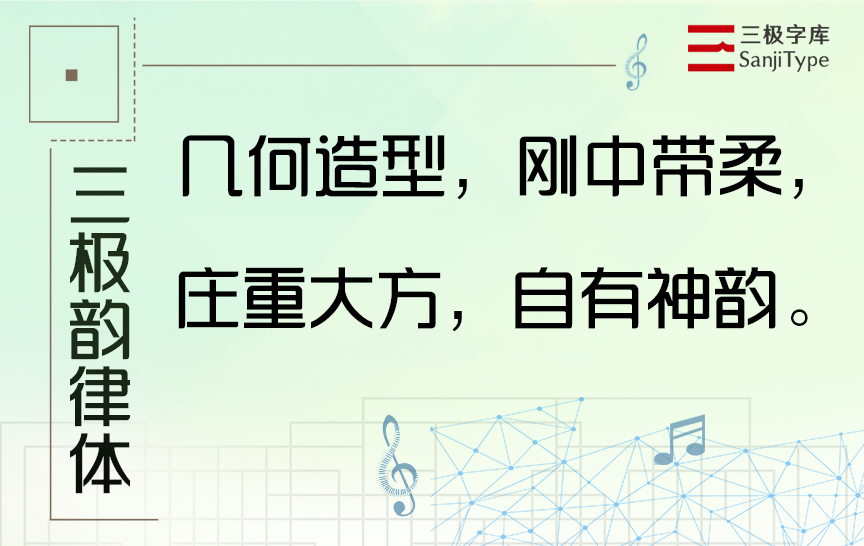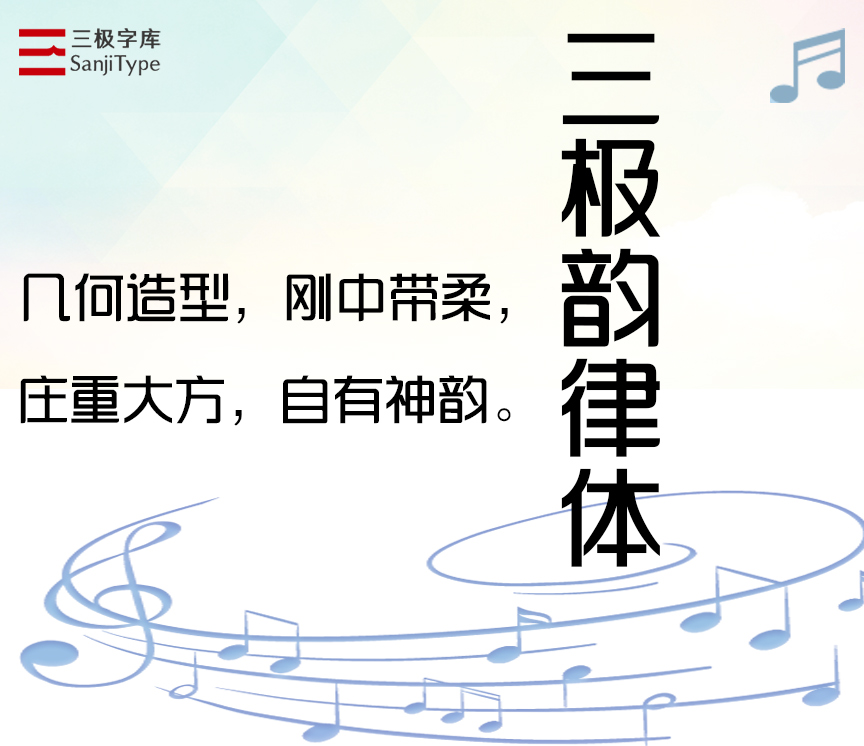
字体名称:三极韵律体
设计师:王荣诚
三极韵律体是一款笔画由几何图形设计构成的创意字体。这款字体的笔画轮廓由直线和转角弧线构成,横竖笔画交叉处、折笔处和部分的收笔处呈四分之一圆弧形状,撇、捺笔画镜像均匀对称,字形充满整个字面框,重心稳定。风格刚中带柔,粗细有秩庄重大方,适用于工艺及家居类品牌的广告和产品包装设计及店面设计。